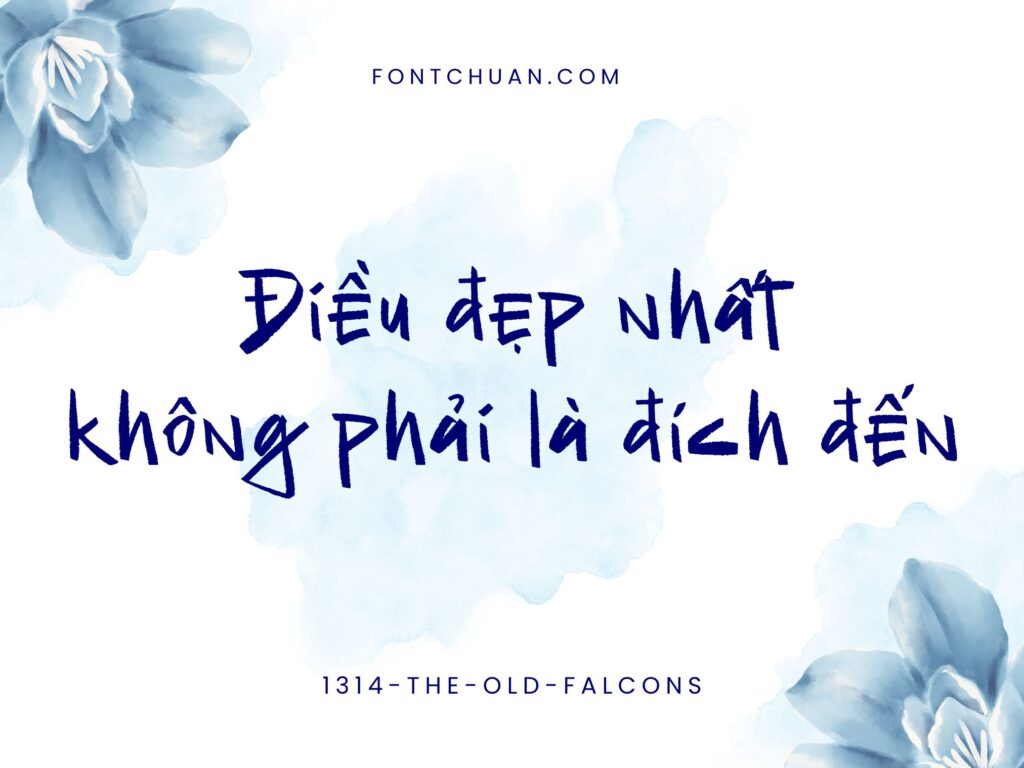
1314-The-Old-Falcons là phiên bản Việt hóa của phông chữ The Old Falcons, được thiết kế bởi Allouse.Studio. Đây là một phông chữ display với phong cách mạnh mẽ và cá tính, mang lại cảm giác nổi bật và sáng tạo cho các thiết kế. Font này đã được FontTiengViet Việt hóa, hỗ trợ đầy đủ các ký tự tiếng Việt, giúp người dùng dễ dàng áp dụng trong các dự án thiết kế đa dạng. Ngoài tiếng Việt, The Old Falcons còn hỗ trợ nhiều ngôn ngữ khác, bao gồm tiếng Anh, Pháp, Tây Ban Nha, Đức và Ý. Phông chữ này được thành viên Font Chuẩn sưu tầm và đăng tải nhằm phục vụ nhu cầu sáng tạo phong phú.
Với phong cách mạnh mẽ và phá cách, 1314-The-Old-Falcons phù hợp cho các ứng dụng như tiêu đề, logo, thiết kế thương hiệu và các ấn phẩm in ấn cần sự nổi bật. Các ký tự có đường nét dày, mang lại sự cá tính và sinh động cho văn bản. Ngoài ra, 1314-The-Old-Falcons còn có thể được sử dụng như một Font chữ công nghệ, lý tưởng cho các dự án liên quan đến website, giao diện ứng dụng, tài liệu kỹ thuật hoặc các sản phẩm công nghệ, mang đến cảm giác hiện đại và chuyên nghiệp. Trong lĩnh vực sự kiện, phông chữ này có thể được sử dụng trong các dịp như lễ hội, thiệp cưới và sinh nhật. 1314-The-Old-Falcons cũng thích hợp cho các ngành nghề như quảng cáo, giáo dục và công nghệ, tạo tính linh hoạt và ứng dụng đa dạng trong nhiều dự án sáng tạo.